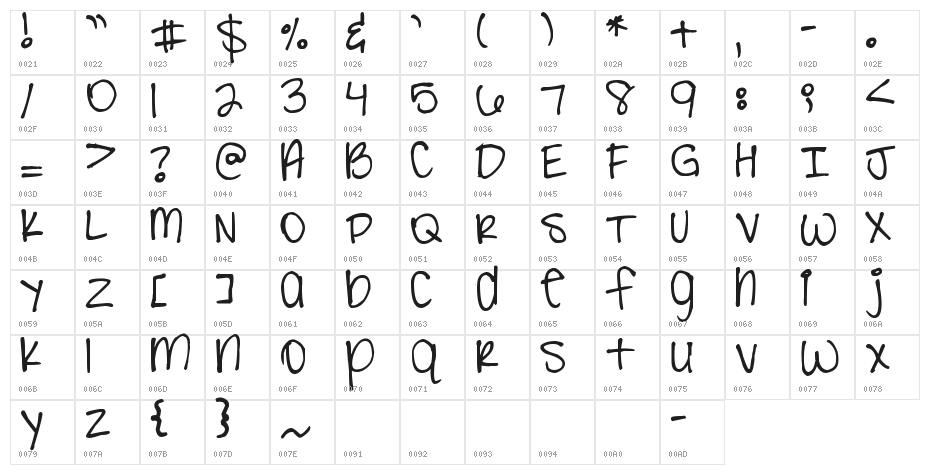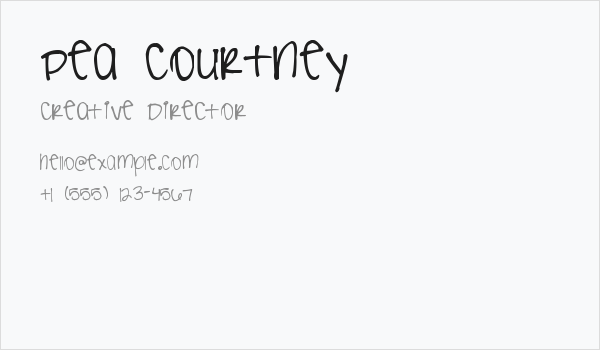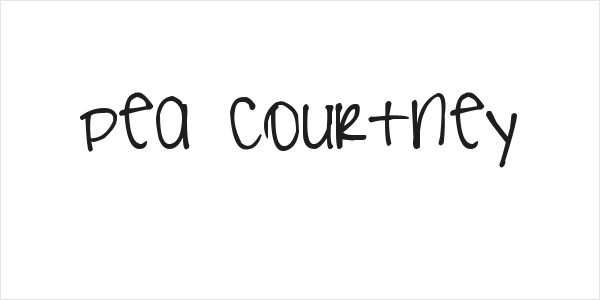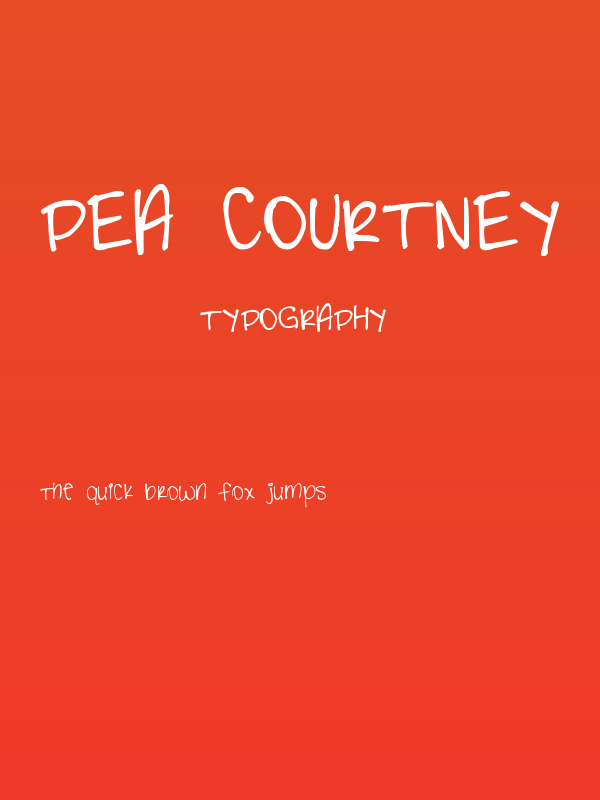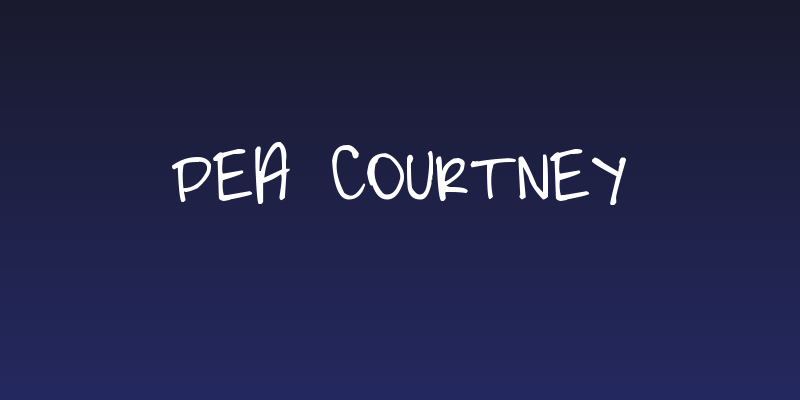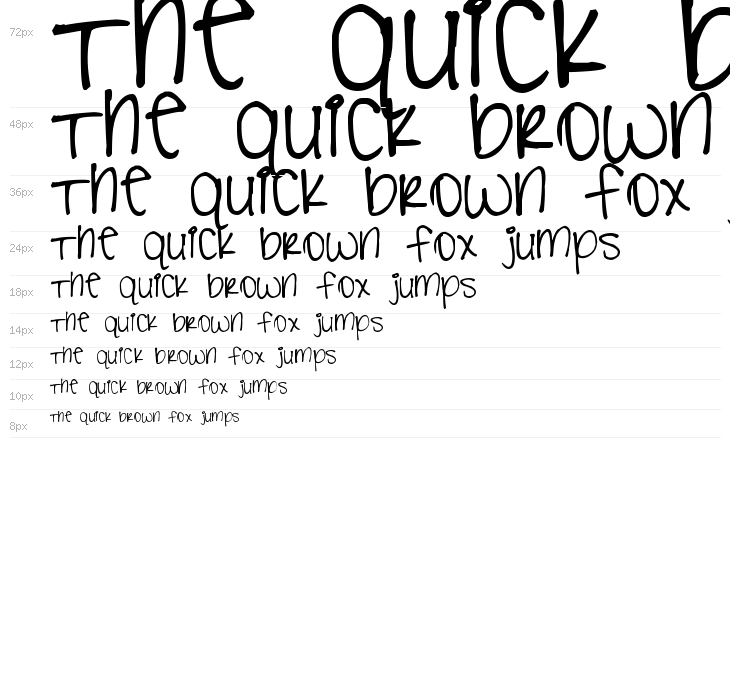
Pea Courtney Font
| Stile generale | Casual, Playful |
| Caso d'uso | Invitations, Greeting cards, Playful branding |
| Progetti proposti | Ideal for invitations, greeting cards, playful branding, and personal projects. |